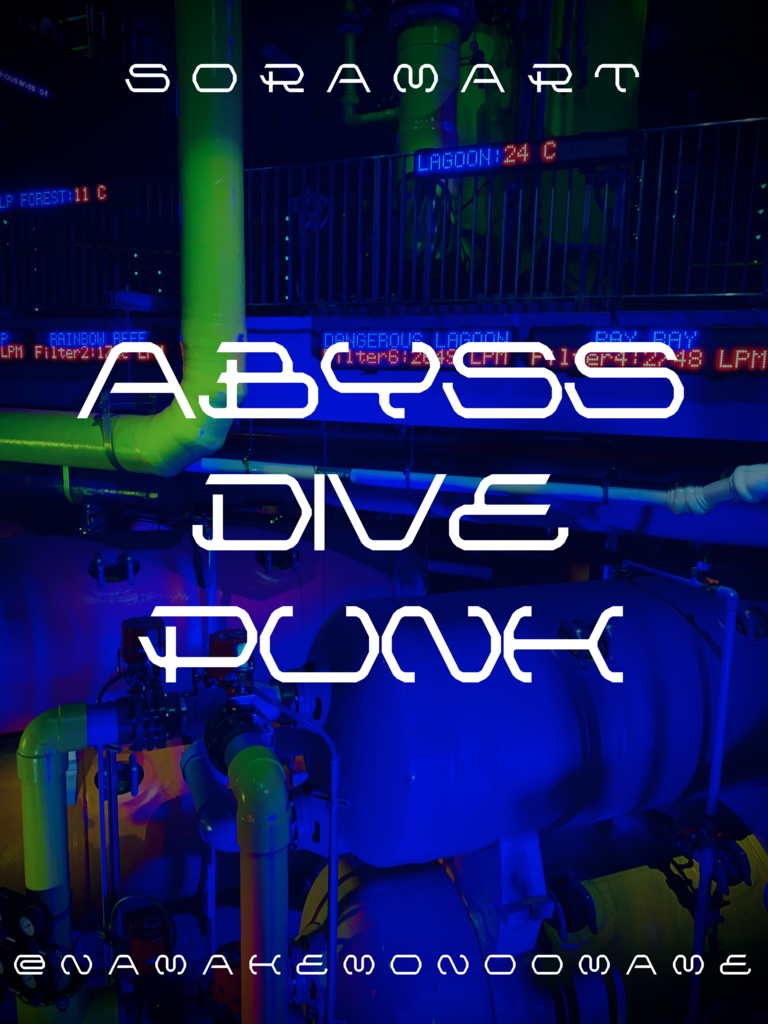
そらマートフォントデータ”Abyss Dive Punk”ダウンロード商品¥ 2,500カートに入れるギフトとして贈る「ギフトとして贈る」とは未知の深海に挑む潜水艦……をイメージした海洋SF風フォント "Abyss Dive Punk" です。 「TrueTypeフォントファイル」という形式です。 ダウンロードした後、Zipファイル内のデータをインストールしてお使いください。 このフォントは商用利用可となっております。 お客様の制作・創作活動のお役に立てれば幸いです。 ※使用上の注意事項などは、添付のReadmeをお読みください。そらマートFANBOX開設中フォント・書体フォントデータ”RANMMA Drive”そらマート¥ 0フォント・書体フォントデータ”Dandy Laser Max”そらマート¥ 2,500フォント・書体フォントデータ”Dandy Laser”そらマート¥ 2,500フォント・書体フォントデータ”Bubblegum Beat”そらマート¥ 2,500フォント・書体フォントデータ”Caltrop Serif LLL”そらマート¥ 2,500フォント・書体フォントデータ”Caltrop Serif LL”そらマート¥ 2,500フォント・書体フォントデータ”Caltrop Serif”そらマート¥ 2,500フォント・書体フォントデータ”Tonik Crate Super Long”そらマート¥ 2,500フォント・書体フォントデータ”Dot Eat Bug Acid”そらマート¥ 2,500フォント・書体フォントデータ”Dot Eat Bug Mild”そらマート¥ 2,500フォント・書体フォントデータ”Dot Eat Bug”そらマート¥ 2,500フォント・書体フォントデータ”Solid Voltage Strike”そらマート¥ 2,500フォント・書体フォントデータ”Solid Voltage”そらマート¥ 2,500フォント・書体フォントデータ”Henge Edge Rock”そらマート¥ 2,500フォント・書体フォントデータ”Henge Edge Tall”そらマート¥ 0フォント・書体フォントデータ”Henge Edge”そらマート¥ 0フォント・書体フォントデータ”Chisel Stroke Wide”そらマート¥ 2,500フォント・書体フォントデータ”Chisel Stroke”そらマート¥ 2,500フォント・書体フォントデータ”Crushed Can Serif Empty”そらマート¥ 2,500フォント・書体フォントデータ”Crushed Can Serif Wide”そらマート¥ 2,500もっと見る